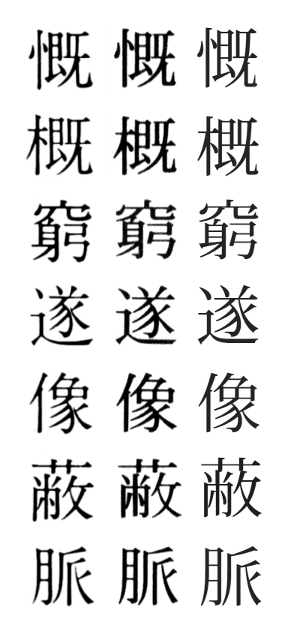
昨日のあれは附属書6を参照したからなのかもしれない、というコメントをいただいたので、90JISで変更された他の漢字についてもちょっと調べてみる。
第一水準の中で、差異に気がついたものを並べてみた。左から順に、JIS X 0208-1983 の規格票の字形、JIS X 0208:1997 の附属書6にある「83」「78-83」の字形、Adobe-Japan1 の83JIS用グリフの字形。
慨・概
附属書6では「旡」の1画目が左に飛び出たまま(90JISと同じ字形)になっている。これについては、AJ1は問題なし。
ただAJ1では、「旡」の最終画の起筆位置が「慨」と「概」でなぜか違う。83JISの規格票に合わせてあるのかと思いきや、むしろ逆になっている。
窮
83JISの規格票では「身」の6画目は横画になっているが、附属書6とAJ1では跳ね上げている。
遂・像
「豕」の最後の2画が、三者とも微妙に違う。
蔽
83JISでは「㡀」の中央部分に墨溜りがあり、縦画が上下2画に分かれている。附属書6ではこの墨溜りがなく、90JISと同じ字形*1。
AJ1については、Adobe Technical Note #5078 にこう書いてある。
(...) the glyphs for CIDs 3603 (Supplement 0) and 13505 (Supplement 4) are identical when rendered with the Kozuka Mincho design, but may be rendered differently for other typeface designs.
小塚明朝じゃ83JISの字形(CID+13505)と90JISの字形(CID+3603)は同じにしてあるけど、区別したけりゃしていいよ、と。
脈
最終画の起筆が上につくか離れるか。……これは微妙か。
というわけで
附属書6とAJ1が同じになっているものもあるけど、全てがそうだというわけではないっぽい。
第二水準についても附属書6をざっと見てみましたが、作字が結構いいかげんなようです。
*1:90JISの「攵」を大きくしただけの、意図のよくわからない作字。